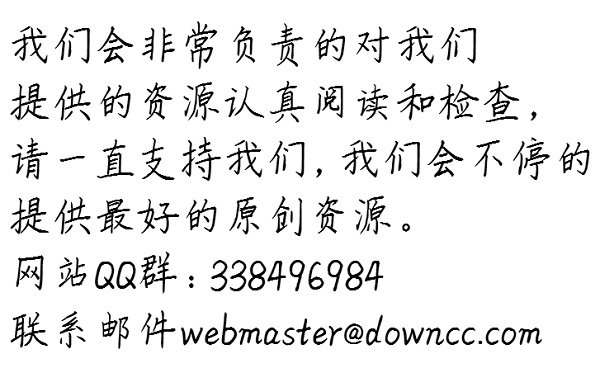
正氣繁楷體是一款美化過后的小寶手寫字體,較原字體使用性更為廣泛,支持繁簡體輸入,給字體更加獨(dú)特的視覺呈現(xiàn),綠色資源網(wǎng)今日推薦!
正氣繁楷體是在小寶手寫簡楷體范本的基礎(chǔ)上,應(yīng)廣大字體迷的要求增加了繁體支持,并重寫優(yōu)化了部分簡體字,本字體是簡繁合體版本。
小寶手寫簡楷體專注于簡體輸入,而正氣繁楷體在簡體的基礎(chǔ)上補(bǔ)充了繁體字庫,讓漢字輸入更加高效,可以使用在更多的平面設(shè)計(jì)場合了!